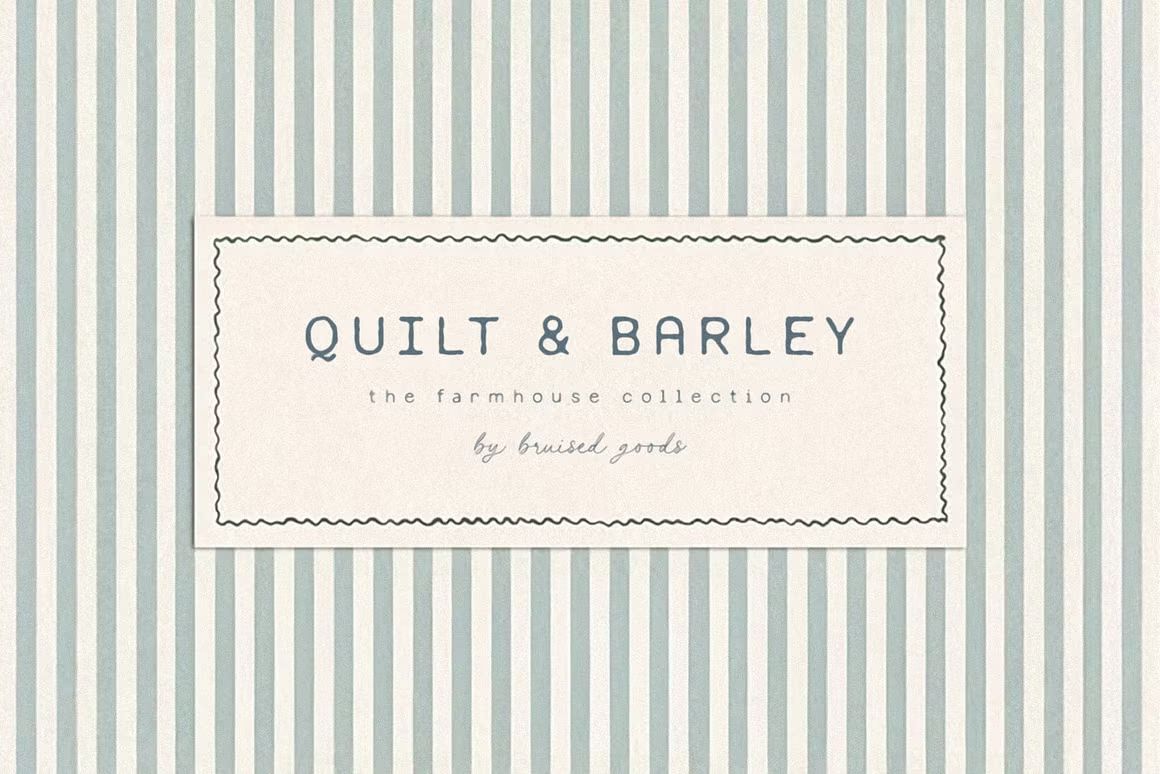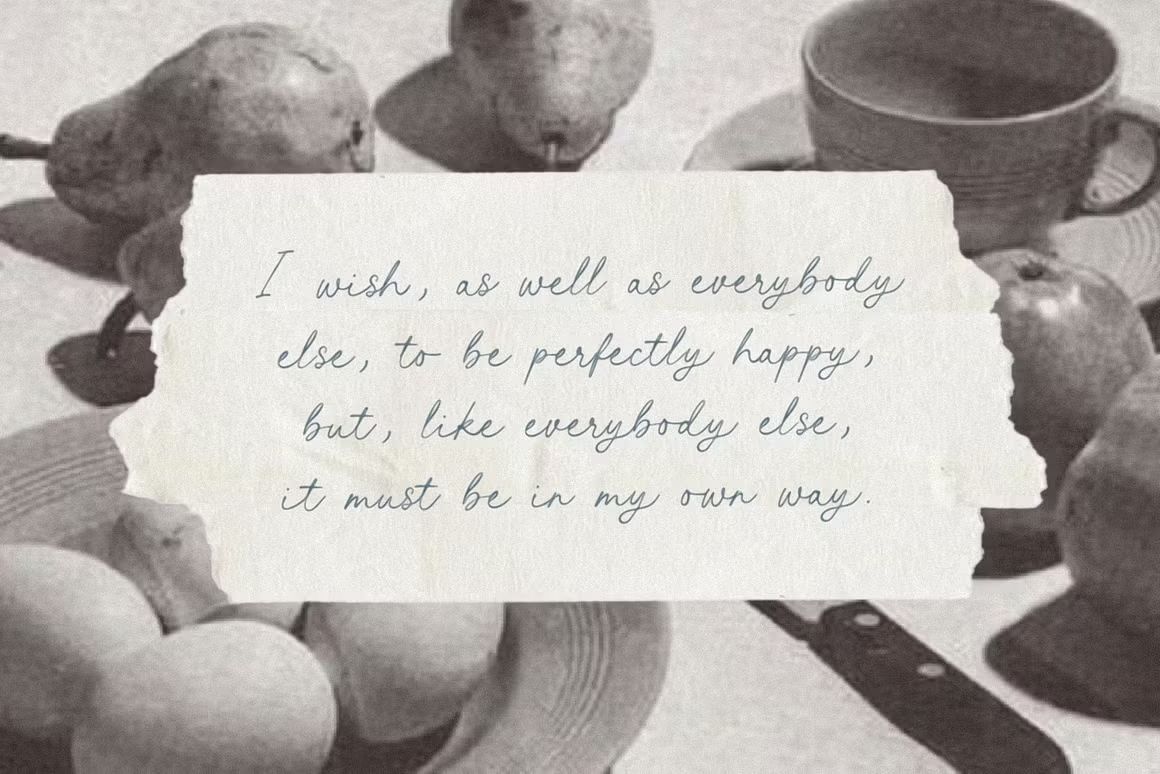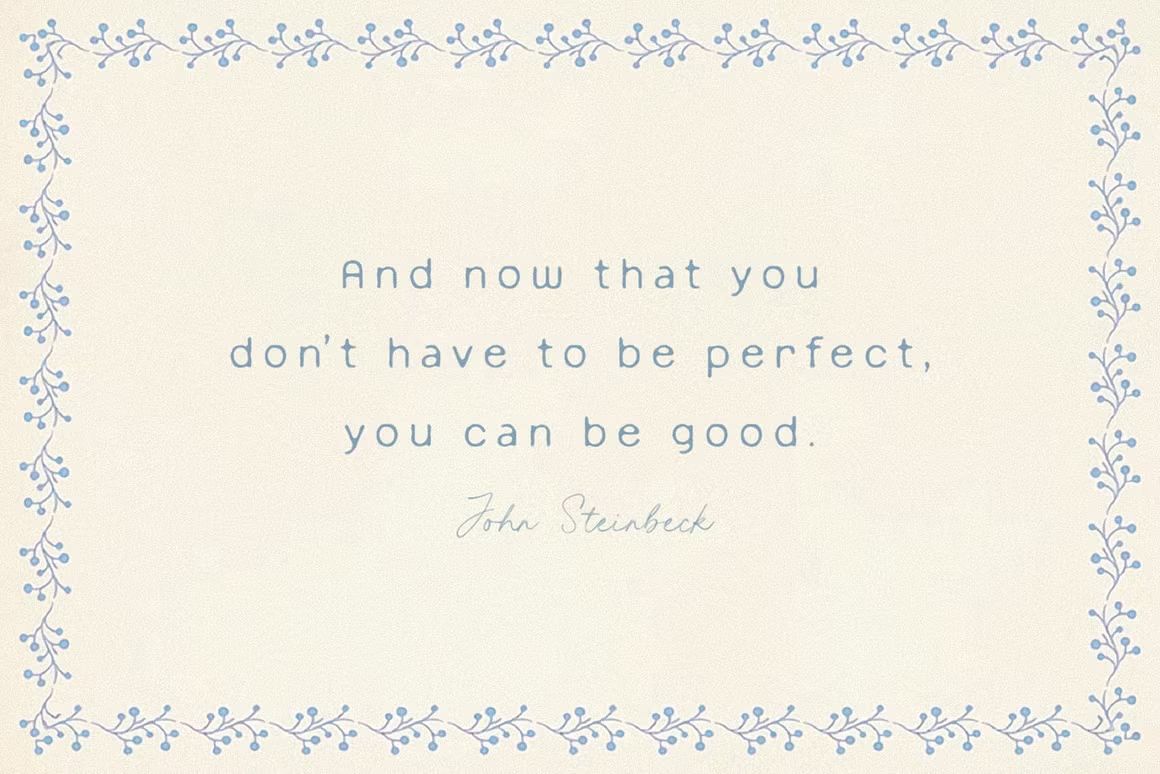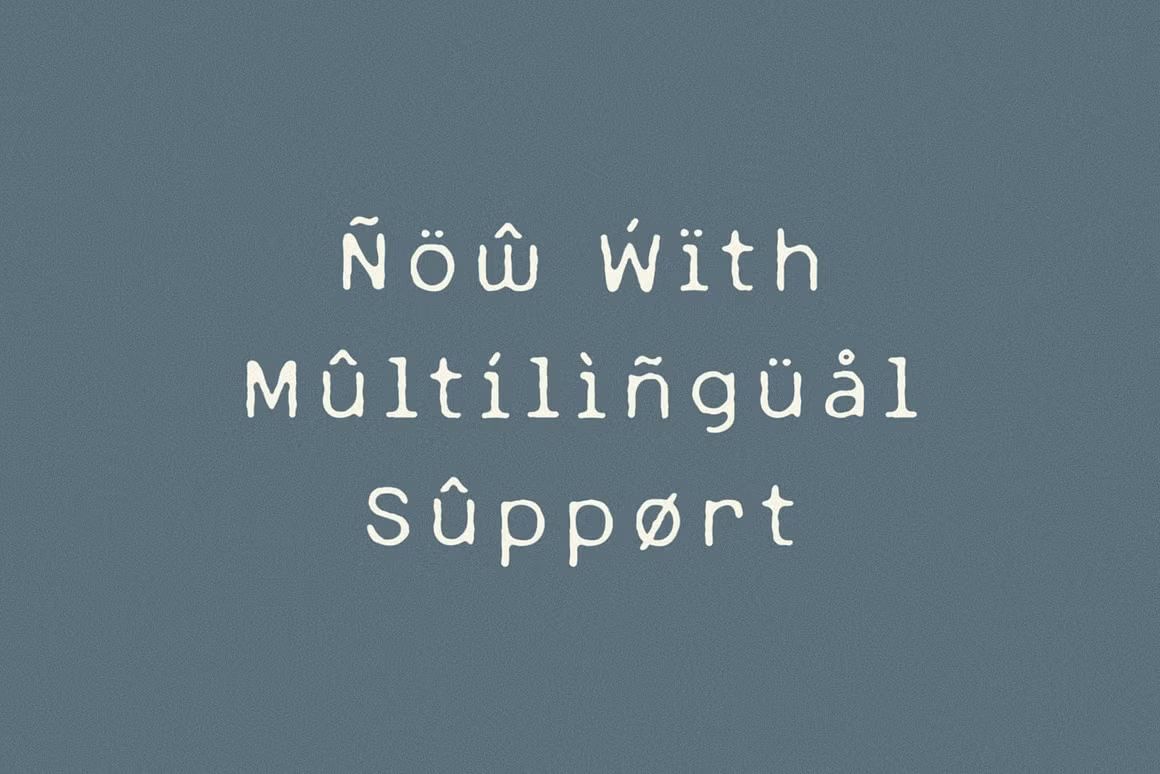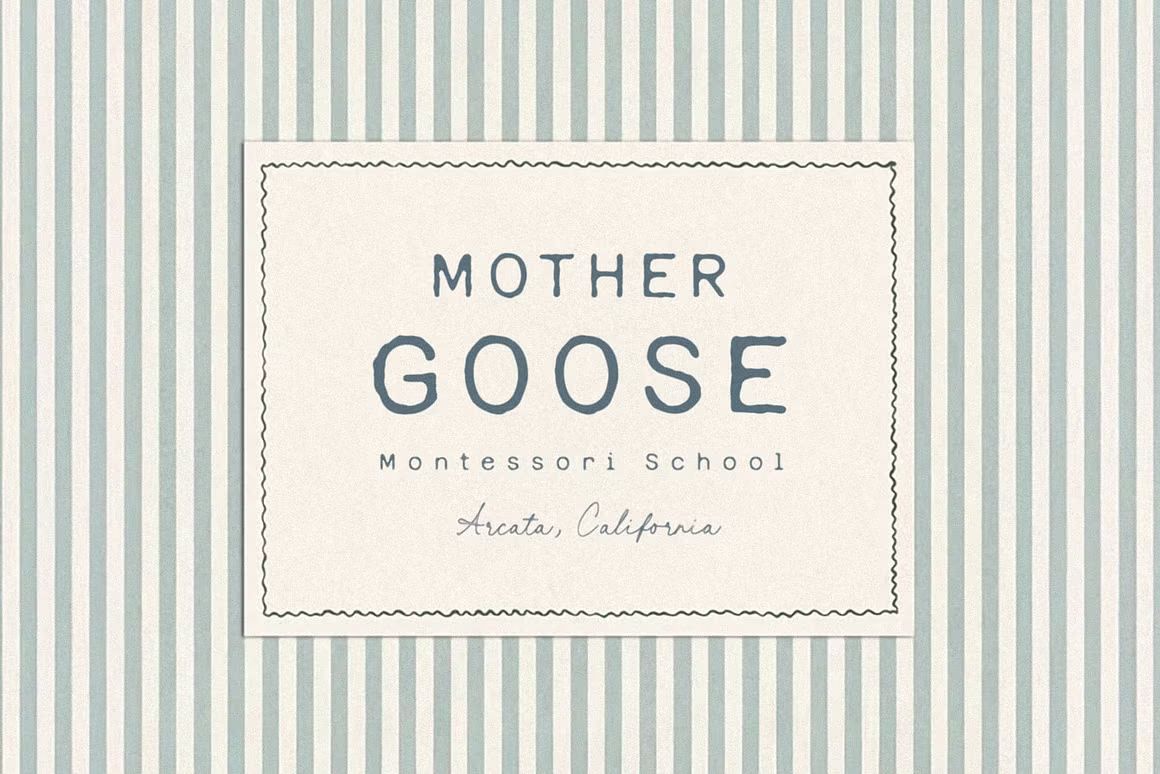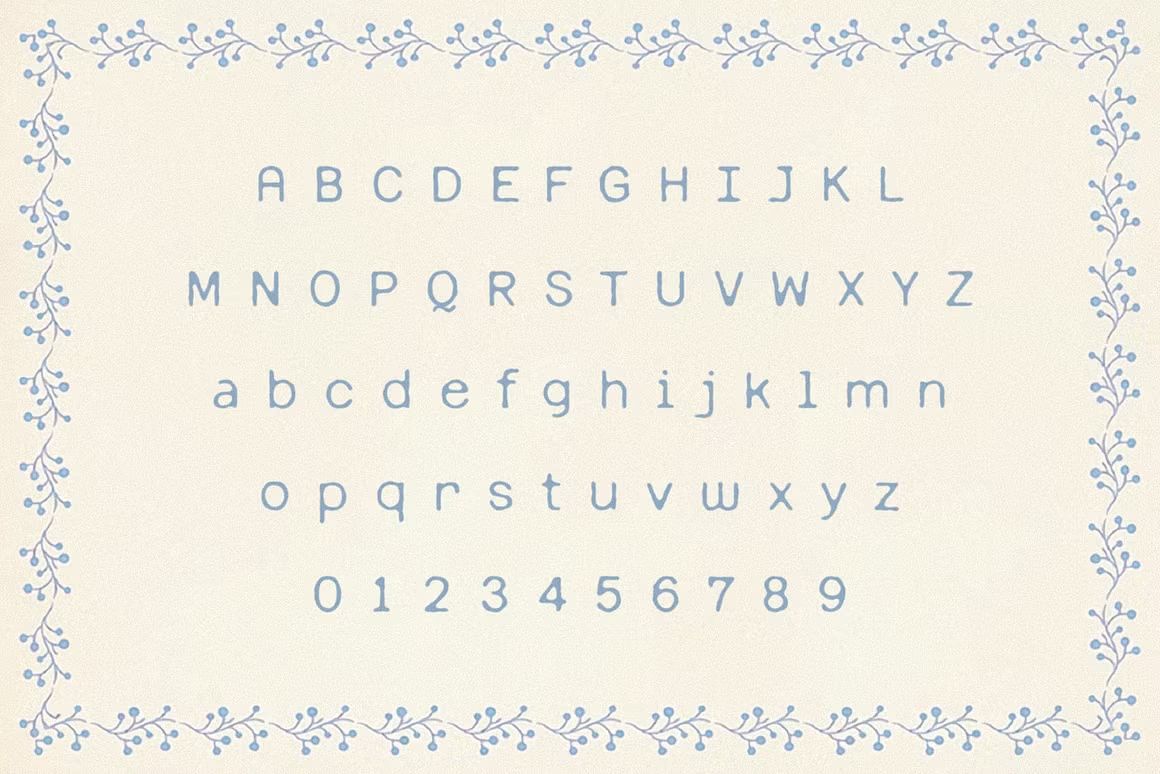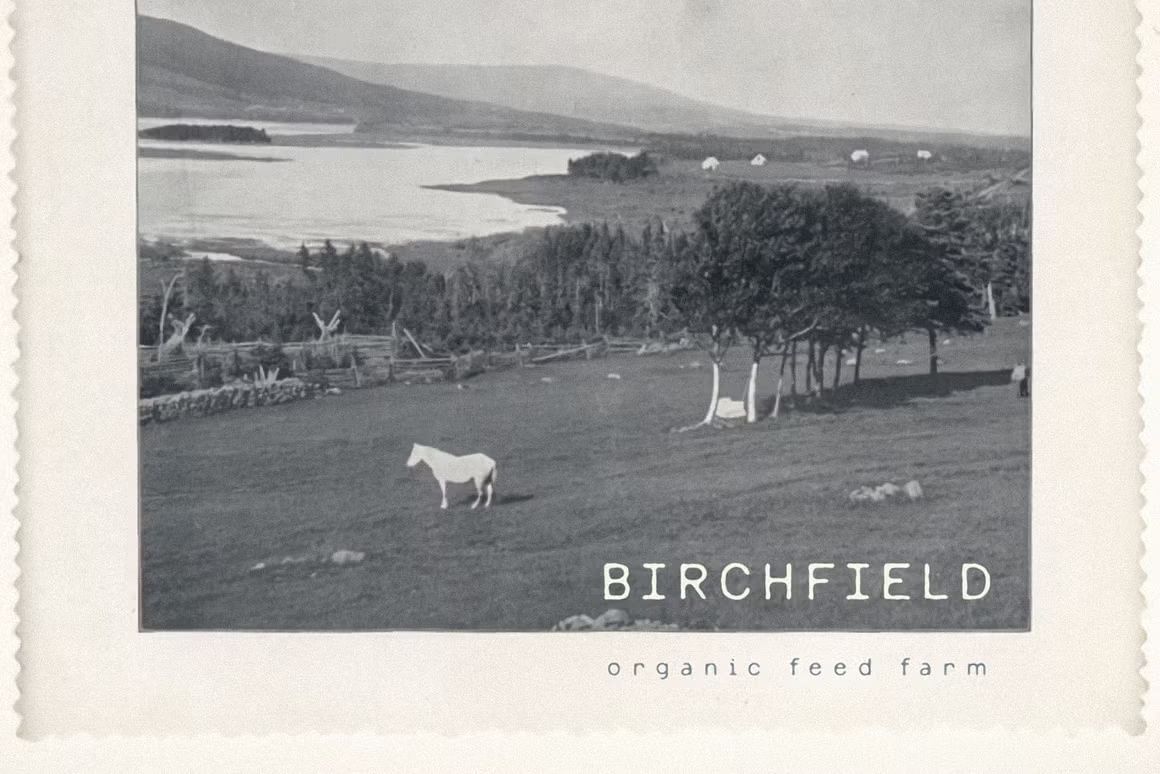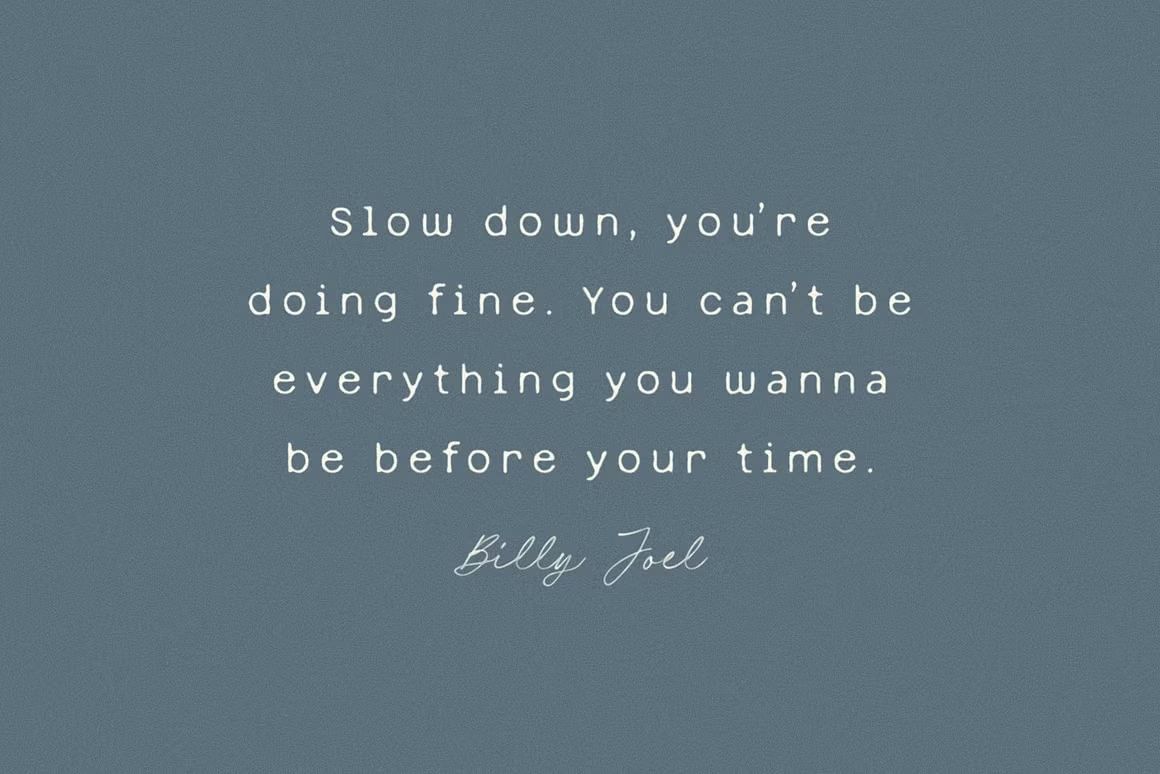
Quilt & Barley – Handwritten Font
Quilt & Barley – Handwritten Font yang elegan dan halus, cocok untuk branding, undangan, logo, dan desain feminin lainnya. Tersedia dalam format OTF dan TTF, mudah digunakan di berbagai software desain.
Quilt & Barley adalah font handwritten bergaya modern calligraphy yang menampilkan goresan halus dan elegan. Font ini cocok digunakan untuk proyek desain seperti branding, undangan, logo, label produk, dan media sosial. Dengan nuansa feminin dan personal, Quilt & Barley mampu memberikan sentuhan artistik dan profesional pada setiap karya.
Fitur unggulan:
• Gaya tulisan tangan modern yang lembut dan anggun
• Cocok untuk desain branding, wedding, logo, dan kemasan
• Mendukung huruf besar, kecil, angka, dan tanda baca